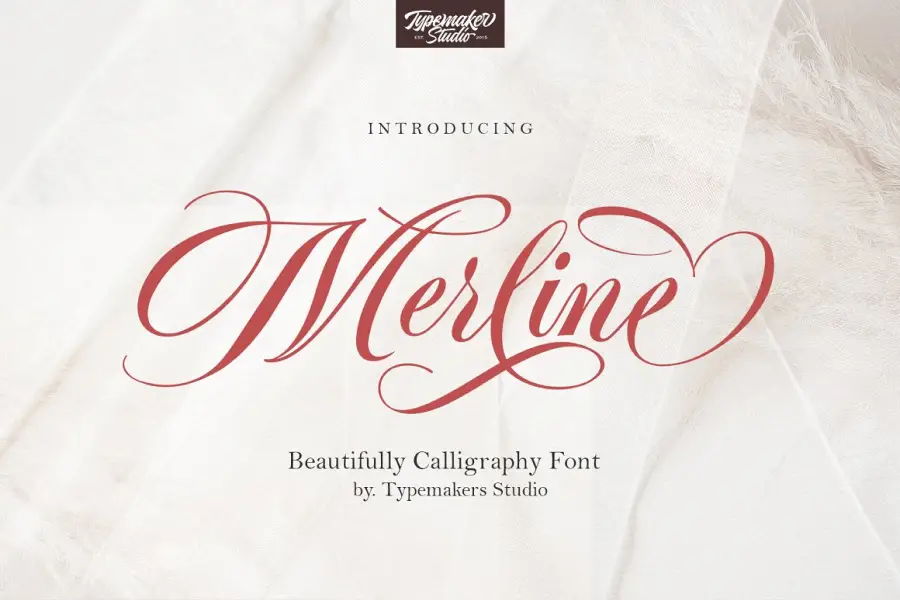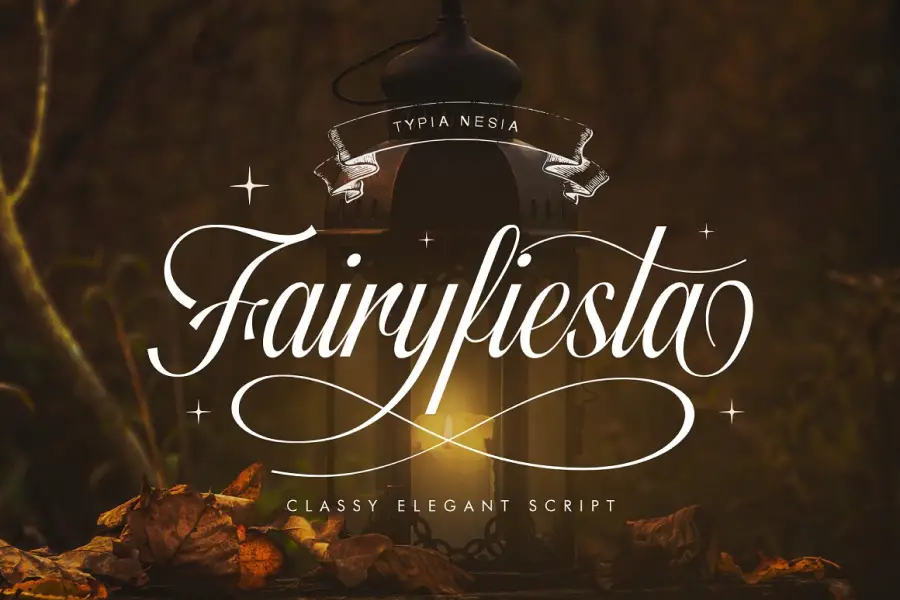
캘리그라피 글꼴에 대해 들어봤지만 어떤 글꼴을 사용해야 하는지, 어디에서 찾을 수 있는지 잘 모르실 수 있습니다. 괜찮아요; 우리는 당신을 덮었습니다!
이 기사에서는 그래픽 디자이너가 디자인을 향상시키는 데 사용할 수 있는 최고의 캘리그라피 글꼴 39개를 공유합니다. 이 글꼴은 아름다울 뿐만 아니라 활용도가 높아 청첩장, 명함, 로고, 포스터 등과 같은 다양한 디자인 프로젝트에 적합합니다.
최근 연구에 따르면 소비자의 92%가 구매 결정에 시각적 요소가 가장 큰 영향을 미친다고 합니다. 아름다운 타이포그래피는 모든 시각적 디자인의 필수 구성 요소이며 캘리그래피 글꼴은 디자인을 나머지 부분과 차별화할 수 있는 우아한 터치를 제공합니다.
따라서 더 이상 고민하지 않고 캘리그라피 글꼴의 세계로 뛰어들어 다음 프로젝트에 가장 적합한 옵션을 찾아봅시다.
최고의 프리미엄 서예 글꼴
이 기사에서는 구매할 수 있는 가장 아름답고 수요가 많은 캘리그라피 글꼴을 소개합니다.
이 글꼴은 청첩장이든 고급 비즈니스를 위한 브랜딩 패키지이든 모든 프로젝트에 품격과 세련미를 더하는 데 적합합니다.
라우터 스크립트
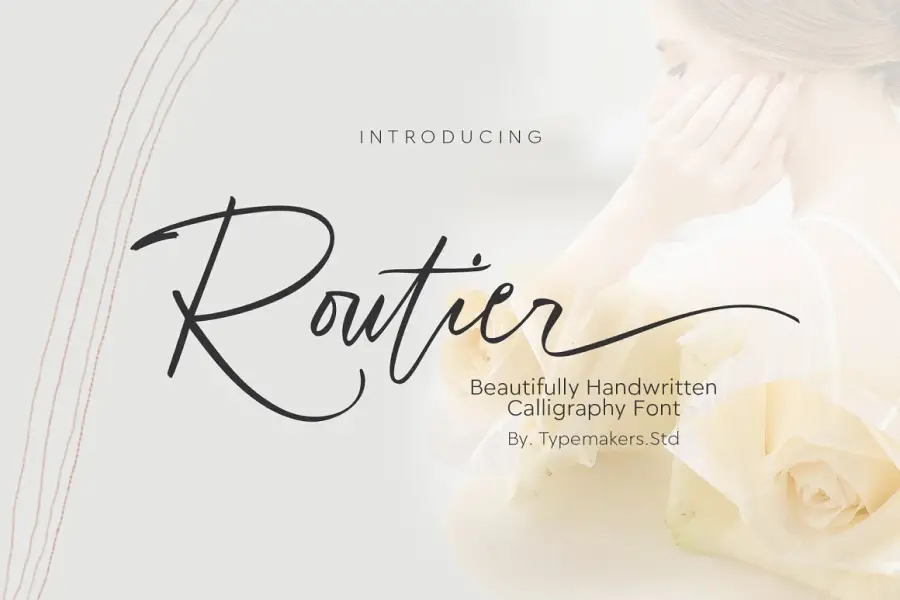
Routier Script는 다양한 디자인 프로젝트에 적합한 자연스러운 손글씨 글꼴입니다. 우아하고 아름다운 미학으로 이 글꼴은 로고, 초대장, 편지지, 결혼식 디자인, 소셜 미디어 게시물, 광고, 제품 포장, 제품 디자인, 라벨, 사진, 워터마크, 특별 이벤트 또는 세련된 터치로 무엇이든 향상시킬 수 있습니다.
이 글꼴은 대문자와 소문자 세트, 160개의 표준 합자, 스타일 대체 및 스타일 세트를 완벽하게 갖추고 있어 사용자 정의 옵션을 통해 고유한 디자인을 만들 수 있습니다. 또한 소문자 및 대문자 대체, 다국어 기호, 숫자 및 문장 부호를 사용하여 프로젝트를 돋보이게 할 수 있습니다.
전반적으로 Routier Script는 다양한 디자인 설정에서 사용할 수 있는 다재다능한 글꼴로 모든 프로젝트에 우아하고 세련된 터치를 제공합니다.
유전
Heredtary는 디자인에 우아함과 세련미를 더할 수 있는 현대적인 캘리그래피 글꼴입니다. 브랜딩, 로고, 결혼식 디자인, 소셜 미디어 게시물, 광고, 제품 포장, 제품 디자인, 라벨, 사진, 워터마크, 초대장 및 문구류를 포함한 광범위한 프로젝트에 적합합니다.
Heredattary의 가장 좋은 점 중 하나는 디자인을 돋보이게 할 수 있는 개인적인 손길을 제공하는 독특한 손글씨 스타일입니다. 이 글꼴은 또한 다양한 디자인을 만드는 데 사용할 수 있는 다양한 문자와 상형 문자를 포함하여 매우 다재다능합니다.
마필라
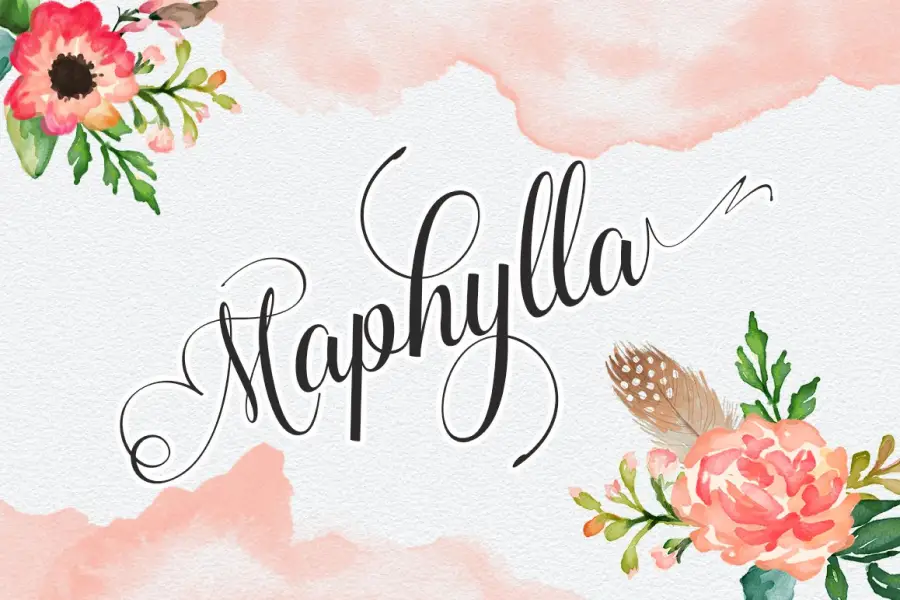
Mapylla는 프로젝트의 디자인을 향상시키려는 그래픽 디자이너에게 완벽한 멋진 독특한 글꼴 스크립트입니다. 이 현대적인 캘리그래피 서체는 우아함과 스타일을 결합하여 모든 창의적인 프로젝트에 탁월한 선택입니다.
총 378개의 글리프가 있는 Maphylla는 디자이너가 선택할 수 있는 다양한 옵션을 제공합니다. 고유한 기능으로 인해 다른 캘리그래피 서체와 차별화되어 디자이너가 자신의 디자인에 진정으로 독특한 터치를 추가할 수 있습니다.
Maphylla의 아름답고 복잡한 디테일은 보는 사람에게 깊은 인상을 남길 것입니다. 이 글꼴은 로고, 초대장, 웹사이트 헤더, 소셜 미디어 게시물 등을 디자인하는 데 적합합니다.
마들리칸 서예
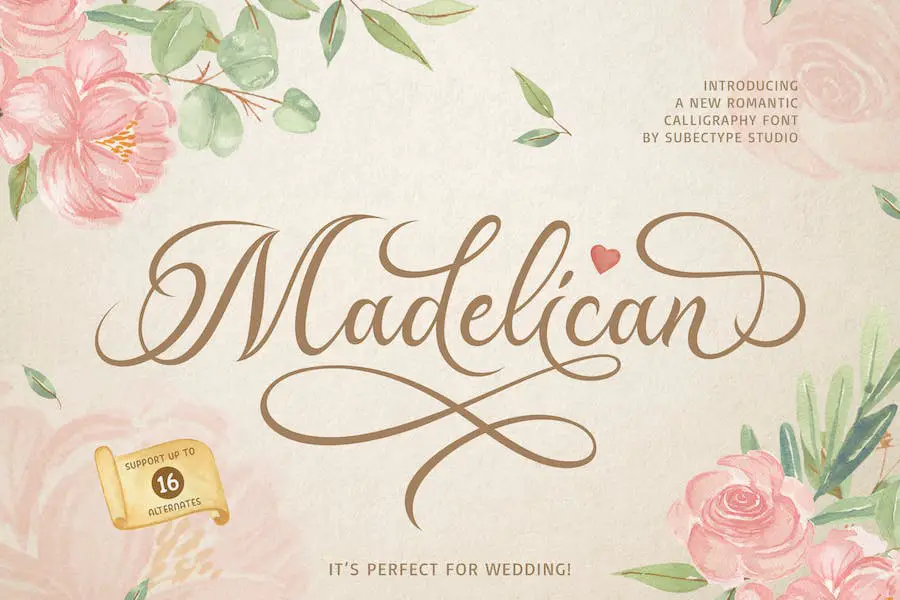
Madelican 서예 글꼴은 현대와 고전 서예의 완벽한 조합입니다. 청첩장, 책표지, 연하장, 로고, 인증서, 브랜딩 등 고급스러움과 격식, 클래식한 스타일을 요구하는 다양한 디자인 작업에 적합합니다. 이 고유한 글꼴에는 수많은 대체 문자가 있어 단 하나의 문자로 다양한 스타일을 쉽게 탐색할 수 있습니다.
이 글꼴의 영감은 이탈리아 여성의 손글씨와 고대 원고에서 나왔습니다. 디자이너는 모던과 클래식 스타일의 완벽한 균형을 이루기 위해 많은 시간과 노력을 들였습니다.
Madelican Calligraphy 글꼴에는 다양한 문자에 대한 다양한 사용자 정의 옵션이 있어 모든 문자가 목적에 적합하고 읽기 쉽도록 합니다.
래스터 서명
래스터 시그니처는 다양한 프로젝트의 디자인을 돋보이게 할 수 있는 손글씨 서체입니다. 자연스러운 획과 곡선이 있는 이 글꼴은 로고, 초대장, 편지지, 결혼식 디자인을 만드는 데 적합합니다. 소셜 미디어 게시물, 광고 및 제품 포장에 사용할 수 있을 만큼 다재다능합니다. 또한 Calligraphy Wedding Fonts는 프로젝트에 적합합니다.
Raster Signature의 가장 좋은 점 중 하나는 소문자 스와시, 다국어 기호, 숫자 및 구두점을 포함하여 전체 대문자 및 소문자 세트와 함께 제공된다는 것입니다. 즉, 추가 문자나 기호를 찾을 필요 없이 아름답고 매력적인 디자인을 만드는 데 필요한 모든 것을 갖추고 있습니다.
샬럿
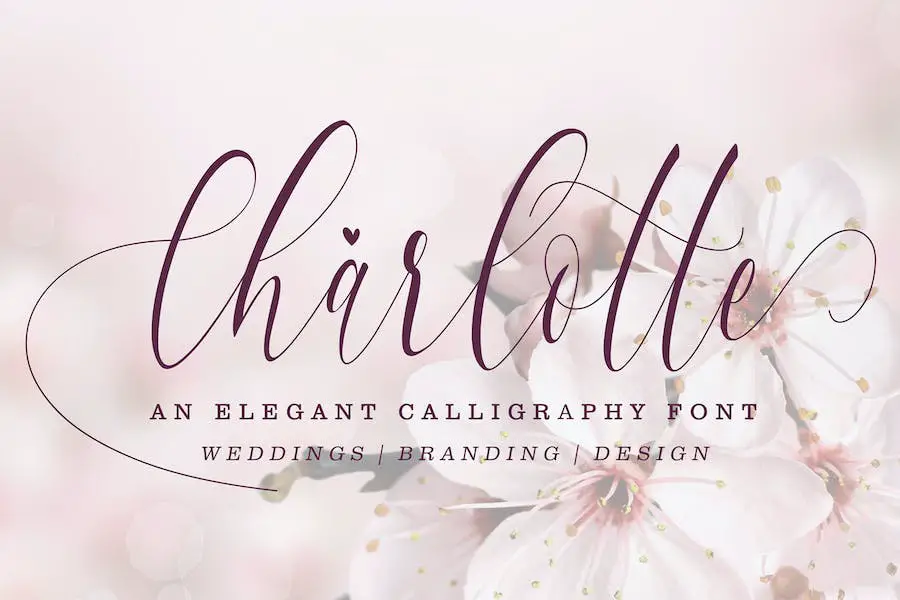
샤롯데 캘리그래피는 모던한 디자인과 사랑의 깊이가 어우러진 아름답고 세련된 서체입니다. 다양한 기준선과 매끄러운 선은 디자인이나 브랜딩에 우아함을 더하려는 모든 사람에게 완벽합니다.
이 글꼴은 제목, 청첩장, 서명, 로고, 티셔츠, 레터헤드, 간판, 레이블, 뉴스, 포스터, 배지 등 다양한 용도로 사용할 수 있습니다.
Charlotte Calligraphy의 독특한 디자인은 시중에 나와 있는 다른 캘리그라피 글꼴과 차별화됩니다. 전통적인 캘리그라피 스타일과 잘 어우러지는 현대적인 트위스트가 있습니다. 이 글꼴의 다양한 기준선과 부드러운 선은 모든 프로젝트에 완벽한 세련된 모양을 제공합니다.
애나벨
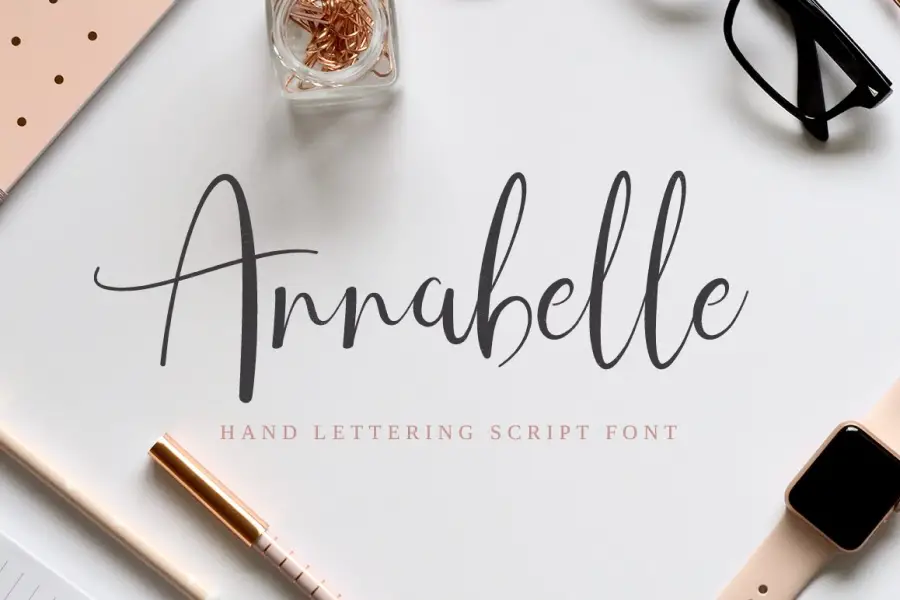
Annabelle은 디자인에 우아함과 세련미를 더하고자 하는 모든 사람에게 완벽한 새로운 서체입니다. 이 손글씨 글꼴은 캘리그라피 스크립트 요소를 염두에 두고 세심하게 제작되어 헤드라인과 로고타입에 이상적입니다. 또한 Word용 서예 글꼴은 프로젝트에 적합합니다.
Annabelle의 눈에 띄는 특징 중 하나는 폭이 혼합된 획과 반복 특성으로 독특한 모양과 느낌을 줍니다. 인쇄 작업을 하든 디지털 프로젝트를 하든 이 글꼴은 디자인 작업에 품격을 더해줍니다.
크리스마스 서예
크리스마스 캘리그래피는 모든 디자인 프로젝트에 화려함을 더해주는 우아하고 세련된 글꼴입니다. 눈부신 포멀 캘리그래피 스타일의 이 글꼴은 멋진 크리스마스 테마 디자인을 만드는 데 적합합니다. 글꼴의 PUA 인코딩을 통해 모든 글리프와 스윕에 쉽게 액세스할 수 있어 초보자도 아름다운 디자인을 간단하게 만들 수 있습니다.
글꼴의 정교하고 황홀한 스타일은 당신의 크리스마스 디자인을 군중들 사이에서 돋보이게 할 것입니다. 정교한 획과 곡선은 모든 프로젝트에 품격을 더할 수 있는 독특한 모양을 제공합니다. 인사말 카드, 초대장 또는 포스터를 디자인하든 관계없이 Christmas Calligraphy 글꼴은 작업을 보다 전문적이고 스타일리시하게 만들어 줍니다.
그라지오사 스크립트
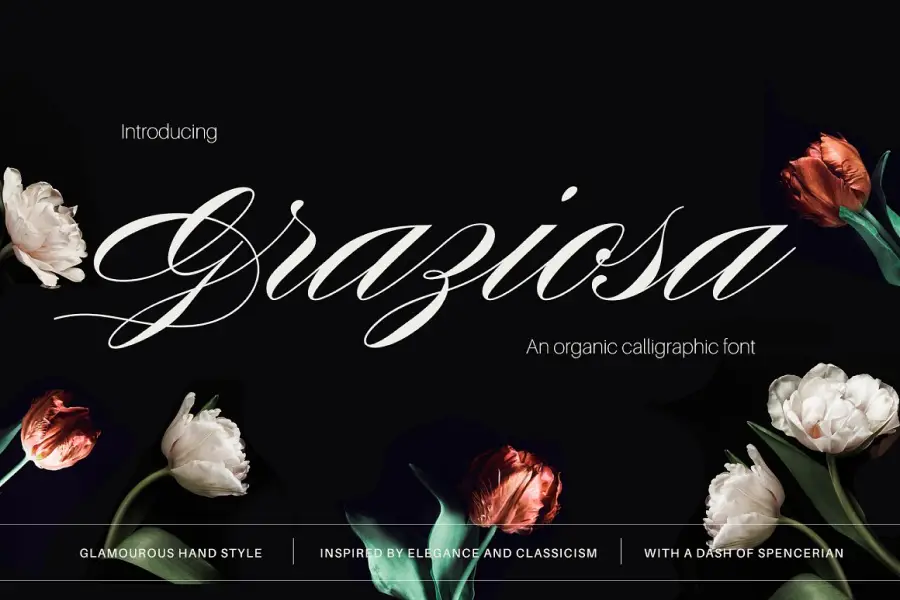
Graziosa Script는 독특하고 유기적인 외관을 위해 고전주의와 Madarasz 스타일을 결합한 캘리그래픽 글꼴입니다. 이 글꼴은 손글씨 터치가 필요한 공식적인 프로젝트에 적합합니다. 또한 전체 대문자 대체 세트를 사용하여 Graziosa Script는 훨씬 더 사실적인 모양을 제공합니다.
이 글꼴은 제품 레이블, 청첩장 및 감사 카드와 같은 특별한 경우에 탁월한 선택입니다. 모든 프로젝트에 개인적이고 우아한 터치를 더합니다. Graziosa Script는 비즈니스 리셉션 및 테이블 번호에도 잘 작동하므로 다양한 용도로 사용할 수 있습니다.
전반적으로 Graziosa Script는 아름답고 기능적인 캘리그라피 글꼴로 사용되는 모든 프로젝트를 향상시킵니다. 고전주의와 유기적인 스타일의 독특한 조화는 작업에 손글씨 터치를 추가하려는 디자이너에게 탁월한 선택입니다. 또한 Canva용 캘리그래피 글꼴은 프로젝트에 적합합니다.
럭셔리원 캘리그래피
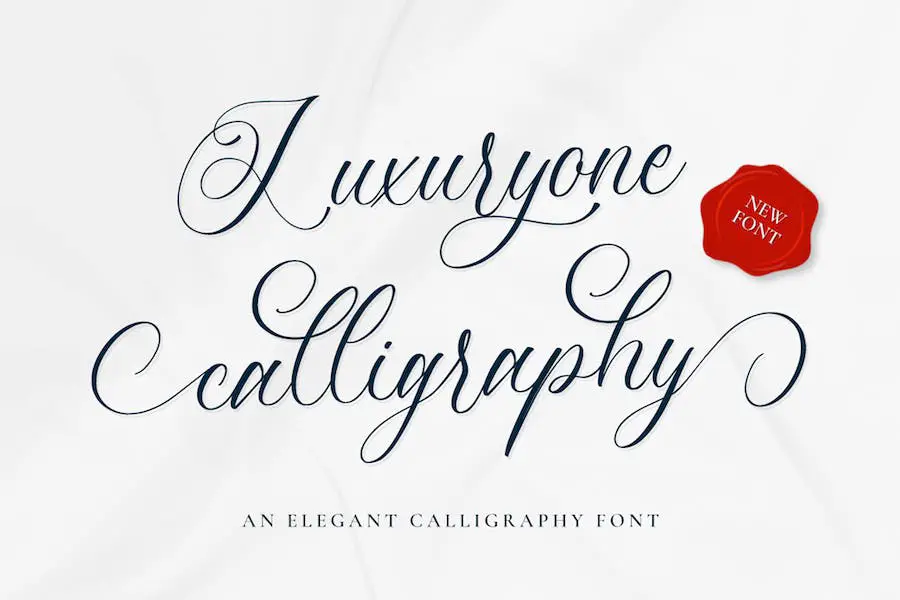
Luxuryone Calligraphy는 세련미와 세련미를 발산하는 멋진 스크립트 글꼴입니다. 이 서체는 프로젝트에 우아함과 매력을 더하려는 디자이너에게 적합합니다. 글꼴의 고유한 디자인은 군중에서 눈에 띄게 만들어 작업을 항상 기억할 수 있도록 합니다.
Luxuryone Calligraphy의 눈에 띄는 기능 중 하나는 PUA 인코딩으로 모든 글리프와 스와시를 쉽게 액세스할 수 있습니다. 이 기능을 사용하면 완전한 창작의 자유를 누릴 수 있으므로 정말 독특하고 멋진 디자인을 만들 수 있습니다. 글꼴의 섬세한 곡선과 가는 선은 청첩장, 브랜딩, 로고 및 기타 여러 디자인 프로젝트에 사용하기에 이상적입니다.
라일라 브리엘
Layla Brielle은 모든 프로젝트에 우아함을 더해주는 정교한 캘리그라피 글꼴입니다. 이 글꼴은 세련된 로고, 고급스러운 웨딩 문구, 스타일리시한 웹 사이트 및 개인 브랜딩 자료를 만드는 데 적합합니다.
Layla Brielle은 숫자와 합자를 포함하여 아름다운 대문자와 소문자의 완전한 세트와 함께 제공됩니다. 소문자에는 우아한 시작과 끝 스와시가 있어 사실적인 손글씨 느낌을 줍니다. Layla Brielle을 사용하면 손쉽게 디자인에 우아하고 세련된 느낌을 더할 수 있습니다.
가장 디자인이 좋은 서예
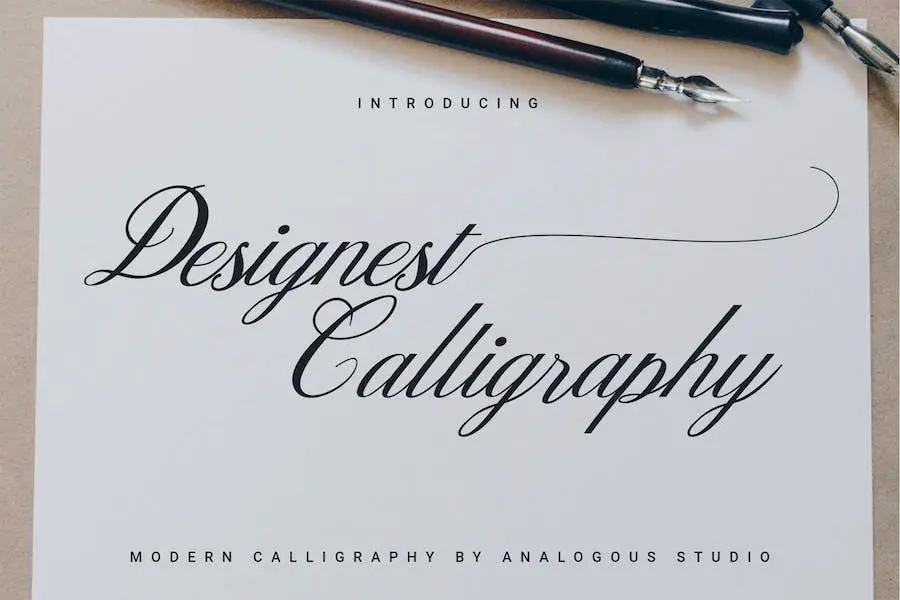
Designest Calligraphy는 스와시, 합자, 대체 문자 및 대부분의 서양 언어에 대한 국제 지원을 포함하는 현대적인 서체입니다. 또한 회로용 서예 글꼴은 디자인에 이상적입니다.
이 글꼴을 사용하면 광고, 판매 자료, 로고, 브랜딩, 포스터 및 소셜 미디어 텍스트 오버레이를 만들기에 완벽한 디자인을 전문적이고 눈길을 끄는 것처럼 즉시 만들 수 있습니다.
결론
결론적으로 디자인 프로젝트를 다음 단계로 끌어올릴 수 있는 최고의 캘리그라피 글꼴 39개를 살펴보았습니다. 클래식하고 우아한 것부터 모던하고 엣지 있는 것까지 이 글꼴은 모든 프로젝트나 분위기에 맞는 다양한 스타일을 제공합니다.